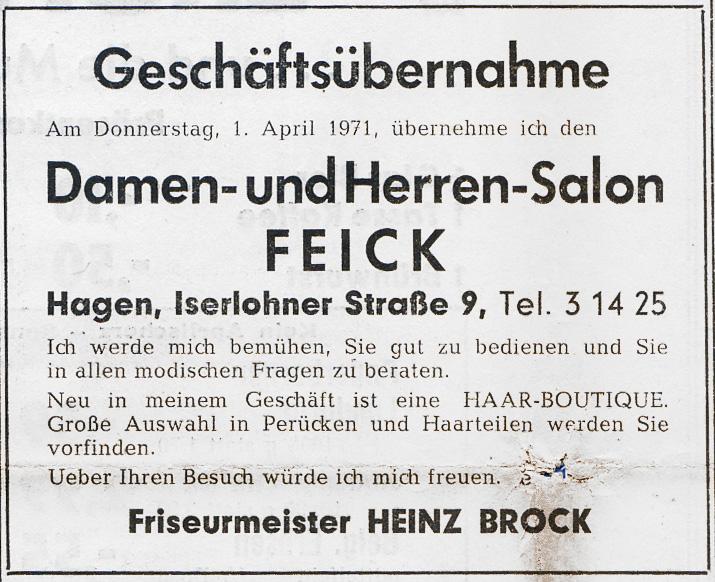
FUTURA DREIVIERTELFETT - alter Schnitt
In alten Druckerzeugnissen kommt die Futura dreiviertelfett immer wieder vor.
Bei heutigen Einsätzen hat die digitalisierte Fassung wenig mit dem
aus der Geometrie entstandenen Grundcharakter zu tun.
Siehe z.B. das kleine "e". Es müsste fast wie das Akzidenz-Grotesk-e aussehen.
Gibt es eine originalgetreue Digitalisierung der dreiviertelfetten Futura?